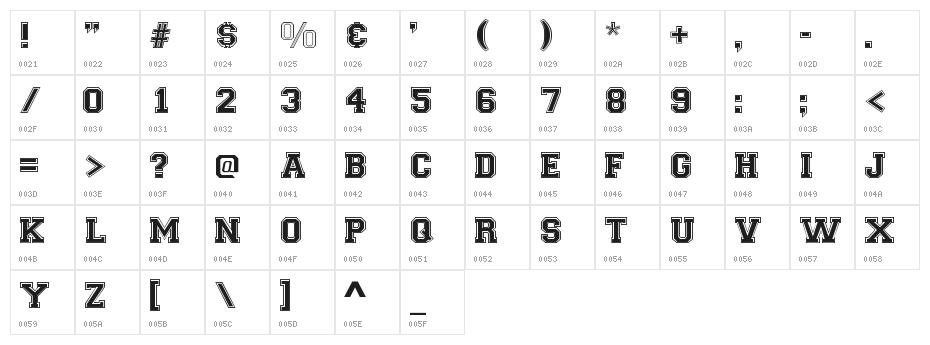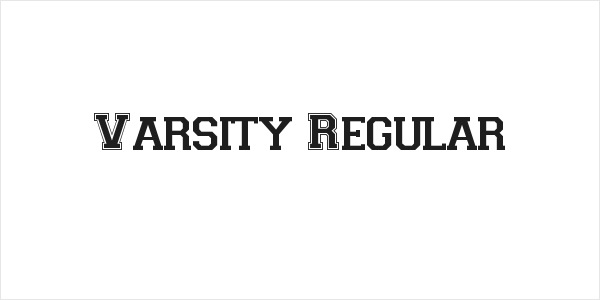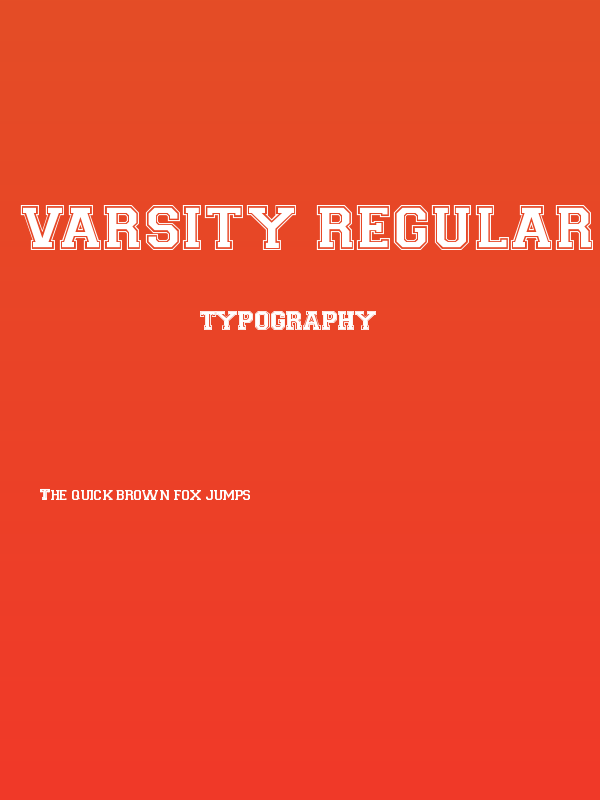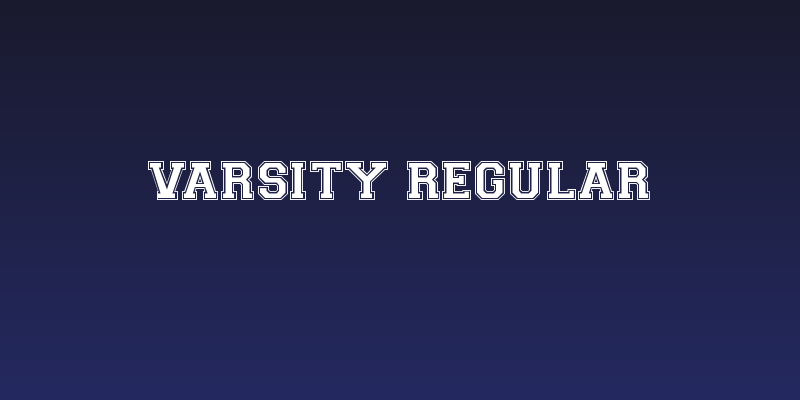
Varsity Regular Font
| Kategorien | Old fashioned |
| Gesamtstil | Classic |
| Vorgeschlagene Projekte | Ideal for sports team logos, school banners, event posters, and merchandise designs. |